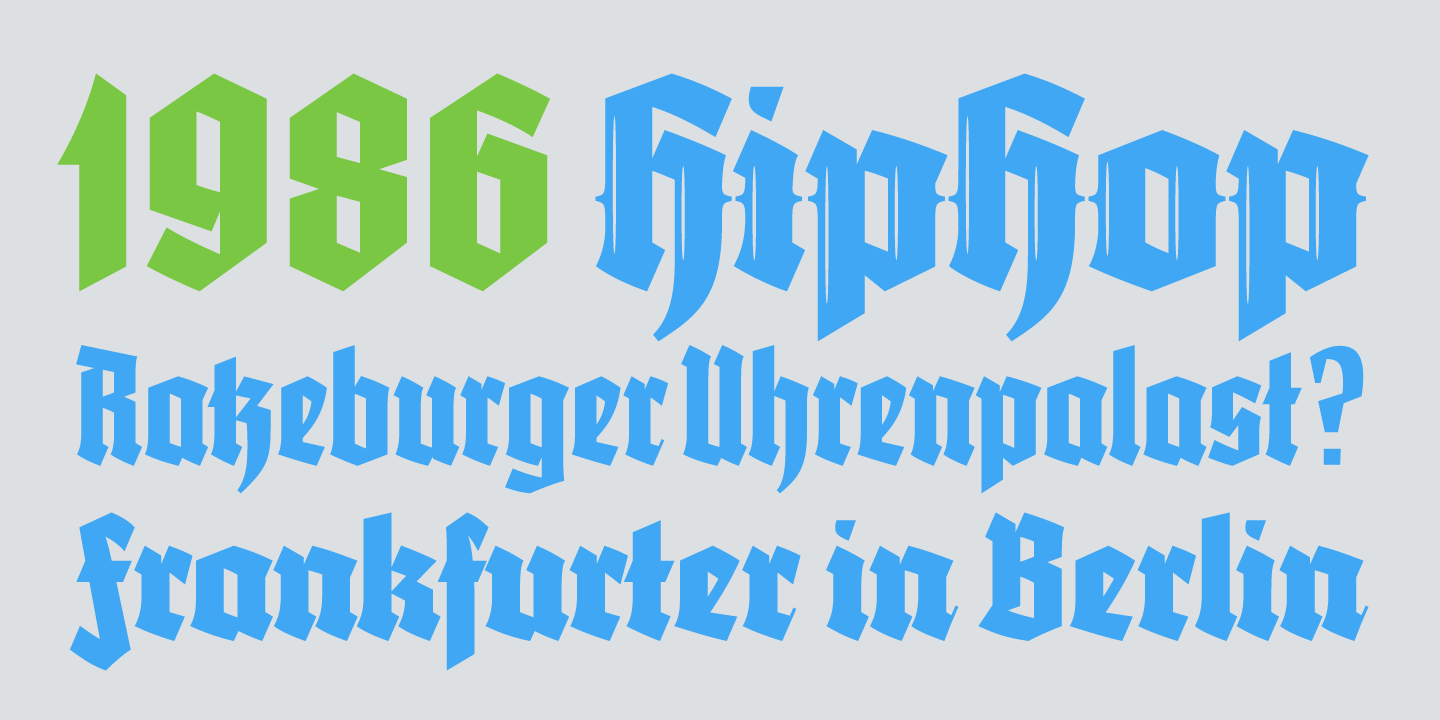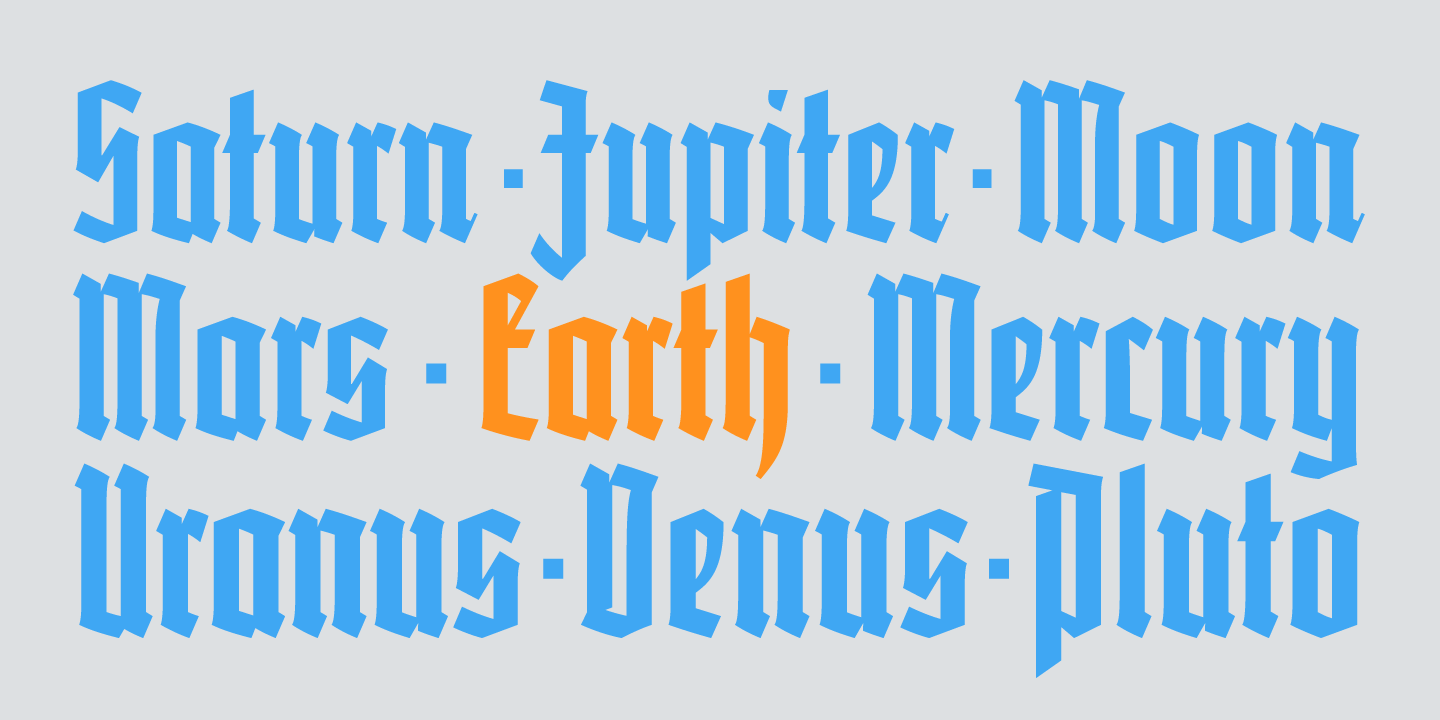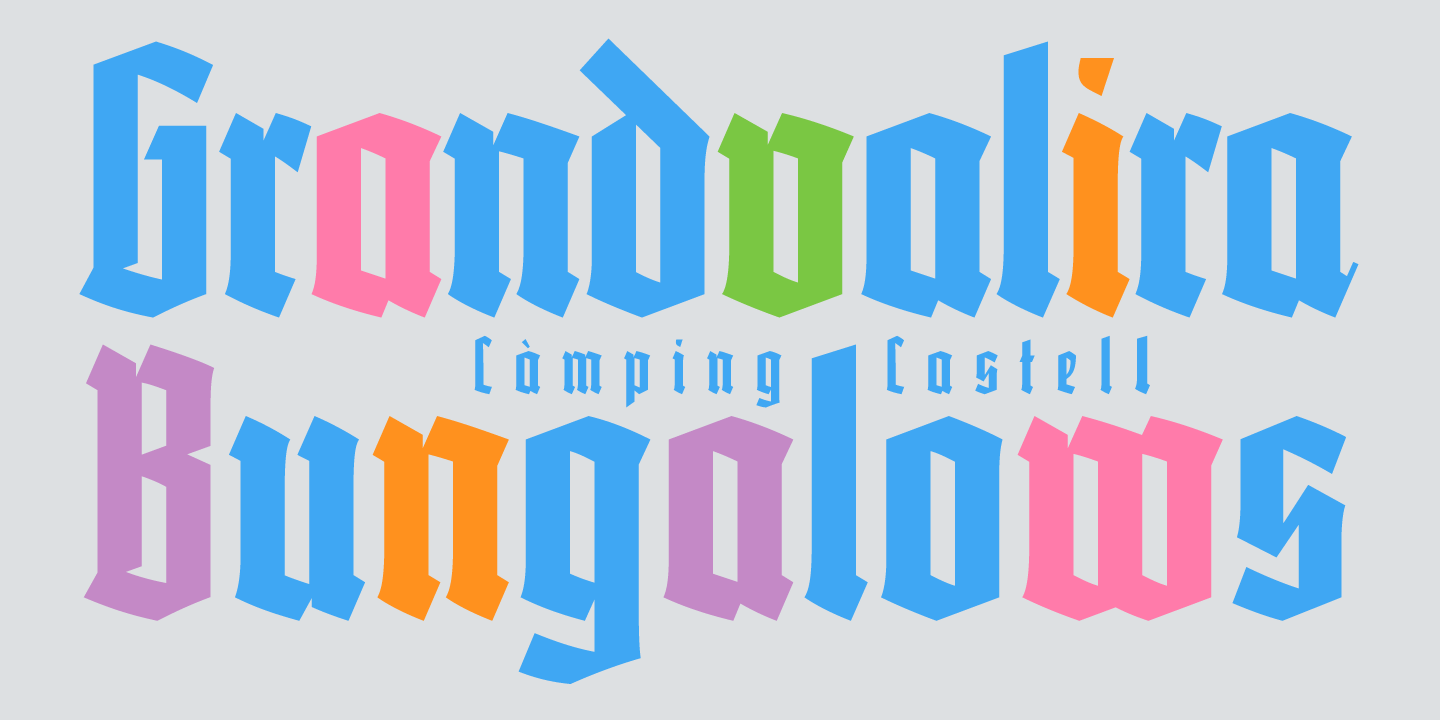
Vivala BL von Johannes Hoffmann ist eine zeitgemäße Umsetzung einer gotischen Schrift in sechs Schnitten: fünf mit unterschiedenen Weiten/Strichstärken und einem fetten lichtem Schnitt. Trotz der Anlehnung an den Stil der schlichten Gotisch, sind die Glyphen auch ohne Fraktursatz-Gewöhnung lesbar und die erweiterte lateinische Belegung ermöglicht einen vielsprachigen Einsatz. Traditioneller Fraktursatz mit den entsprechenden Ligaturen ist aber ebenso möglich.